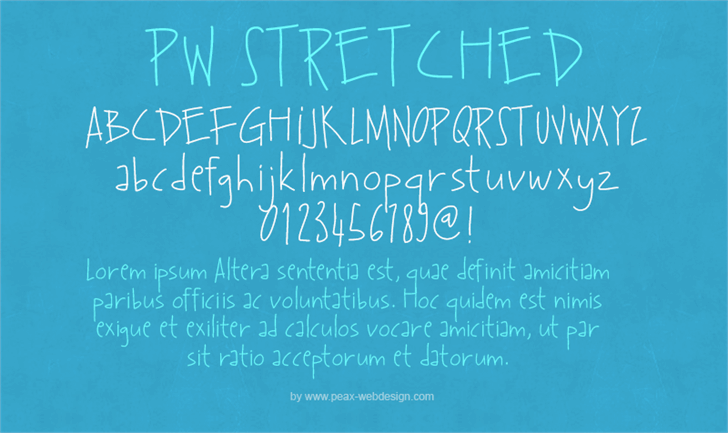
PWStretched Font – Fonte Grátis
PWStretched Font
A ‘PWStretched Font’ é uma elegante fonte escrita a mão criada pelo designer Peax Webdesign. Conhecida principalmente para seus detalhes meticulosamente elaborados, essa fonte oferece um toque natural e autêntico ao seu design. Ideal tanto para projetos pessoais quanto para aqueles que desejam dar vida à sua marca de maneira única e sofisticada. Para usuários que procuram incorporar a fonte em seus trabalhos comerciais, Peax Webdesign pede um contribuição financeira. O valor não é uma barreira; ao contrário, ele reconhece o esforço criativo envolvido na criação da fonte e oferece um apoio valioso para manter a qualidade excepcional dessa fonte de escrita a mão. Esta fonte é perfeita para designers que buscam personalidade em seus projetos digitais. Não apenas sua aparência, mas também o fato de poder usá-la gratuitamente para projetos pessoais sem qualquer restrição, torna-a uma opção excepcional entre as diversas fontes de escrita a mão disponíveis no mercado. Seja você um designer freelance ou profissional, essa fonte é um investimento valioso que vai adicionar seu toque único aos seus trabalhos. Aqui estão algumas características que o fazem tão especial: linhas finas e espessadas bem equilibradas, alongamento perfeito de letras e espaçamento uniforme. A ‘PWStretched Font’ é um complemento perfeito para qualquer projeto digital que busque tanto originalidade quanto elegância, tornando-a uma fonte indispensável não apenas para profissionais em design, mas também para todos os amantes da criatividade na internet.